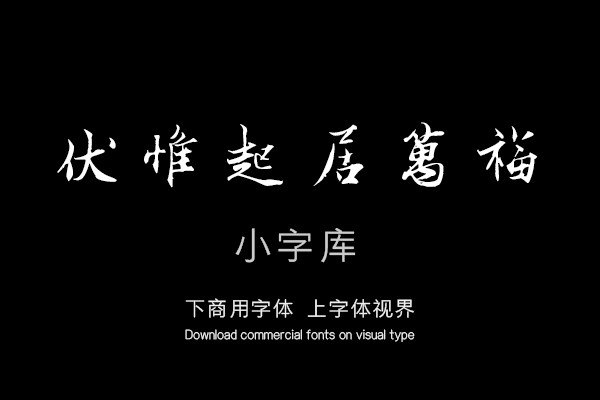
汉标范仲淹行书二札帖
二札即边事、远行二帖,为两通书札。 此两帖书法瘦硬方正,清劲中有法度。人常将此书风喻其人品,称“公书庄严清澈,信如其品”。
边事帖又称乡曲帖   “仲淹再拜,知府刑部仁兄:伏惟起居万福。施乡曲之惠,占江山之胜,优哉乐乎。此间边事,夙夜劳苦。仗朝廷威灵,即目宁息,亦渐有伦序。乡中交亲俱荷大庇,幸甚。师道之奇,尤近教育,乞自重,自重。不宣。仲淹拜上,知府刑部仁兄左右。三月十日。”  远行帖也称修答帖   “仲淹再拜,运使学士四兄:两次捧教,不早修答,牵仍故也。吴亲郎中经过有失款待,乞多谢。吾兄远行,瞻恋增极,万万善爱,以慰贫交。苏醖五瓶,道中下药。金山盐豉五器,别无好物,希不责。不宣。仲淹再拜,景山学士四哥。八月五日。”